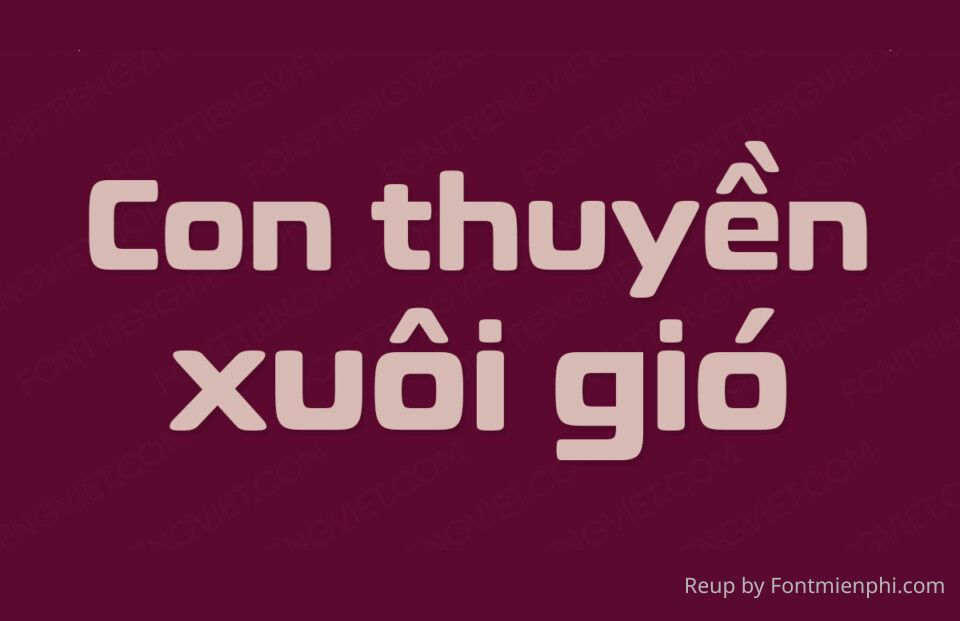
Bạn đang tìm kiếm một bộ font mang đậm chất công nghệ, hiện đại và có chút hơi hướng gaming để làm nổi bật dự án thiết kế của mình? Đừng bỏ qua siêu phẩm 1FTV VIP Valve – bộ font đang được giới Designer săn đón nhiệt tình!
Lấy cảm hứng từ những đường nét mạnh mẽ và sự tối giản ấn tượng, bộ font này hứa hẹn sẽ mang đến một làn gió mới, giúp các ấn phẩm của bạn trông chuyên nghiệp và cá tính hơn bao giờ hết.
🌟 Tại sao 1FTV VIP Valve lại “đốn tim” các Designer?
• Thiết kế đậm chất viễn tưởng & công nghệ: Các nét chữ được thiết kế dứt khoát, góc cạnh nhưng vẫn giữ được sự mượt mà cần thiết. Rất phù hợp với các chủ đề mang tính tương lai (Futuristic), eSports, hoặc công nghệ cao.
• Việt hóa chuẩn xác, chỉn chu: Được thực hiện bởi đội ngũ 1FTV (1Font Việt), font đã được xử lý kỹ lưỡng các dấu câu Tiếng Việt. Bạn có thể thoải mái gõ Tiếng Việt mà không lo tình trạng lỗi font, lệch dấu hay mất cân đối.
• Gia tăng sự chú ý (Attention-grabbing): Trọng lượng font (weight) lớn và rõ ràng giúp 1FTV VIP Valve cực kỳ nổi bật khi được đặt làm Tiêu đề (Heading) hoặc Typography chính.
• Độc quyền & Chất lượng VIP: Đúng như tên gọi “VIP”, bộ font này sở hữu những đường nét được tinh chỉnh tỉ mỉ nhất, đảm bảo ấn phẩm của bạn không bị đại trà.
🎨 Ứng dụng hoàn hảo trong thiết kế
Với đặc thù hình dáng mạnh mẽ, 1FTV VIP Valve là “vũ khí tối thượng” cho các trường hợp sau:
1. Thiết kế Gaming & eSports: Làm logo team, banner giải đấu, hoặc UI/UX cho các tựa game hành động.
2. Poster & Banner sự kiện: Đặc biệt là các sự kiện âm nhạc EDM, sự kiện ra mắt sản phẩm công nghệ (laptop, điện thoại, linh kiện máy tính).
3. Typography ấn tượng: Kết hợp cùng các hiệu ứng như Neon, Glitch hay Cyberpunk để tạo ra các tác phẩm nghệ thuật độc đáo.
4. Thiết kế bao bì: Dành cho các sản phẩm hướng tới giới trẻ, năng động và phá cách.
💡 Mẹo nhỏ khi sử dụng
Lưu ý: Vì đây là một font chữ có cá tính rất mạnh và khá dày, bạn nên sử dụng 1FTV VIP Valve cho các dòng Tiêu đề (Headline) hoặc các cụm từ cần nhấn mạnh. Hãy kết hợp nó với một font chữ không chân (Sans-serif) mỏng và đơn giản hơn cho phần nội dung (Body text) để tạo sự tương phản và giúp người xem dễ đọc hơn nhé!